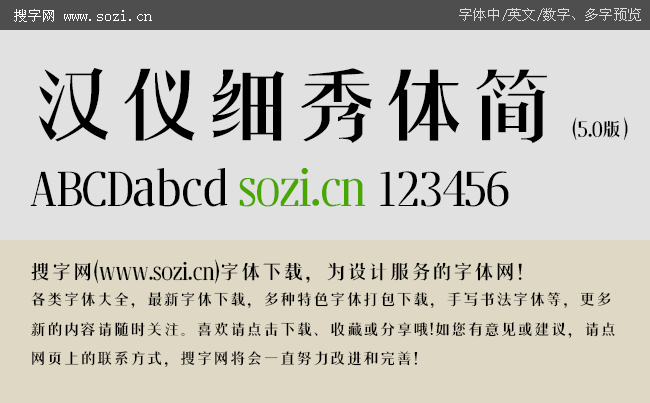
漢儀細(xì)秀體簡
搜字網(wǎng)給大家提供一款漢儀細(xì)秀體簡中文字體下載。漢儀細(xì)秀體字形結(jié)構(gòu)穩(wěn)定,配合設(shè)計(jì)簡潔的筆畫,排版時(shí)整體線性效果更加突出,使閱讀更加流暢。 筆畫風(fēng)格上融合了黑體與宋體的特征,線條簡潔,氣質(zhì)圓柔、秀美,風(fēng)格靈動(dòng)、時(shí)尚。筆畫間的相互呼應(yīng)更使得字體整體結(jié)構(gòu)統(tǒng)一完整、避免了結(jié)構(gòu)的呆板、生硬?蓱(yīng)用于平面設(shè)計(jì)、出版印刷、廣告設(shè)計(jì)、包裝設(shè)計(jì)等領(lǐng)域。